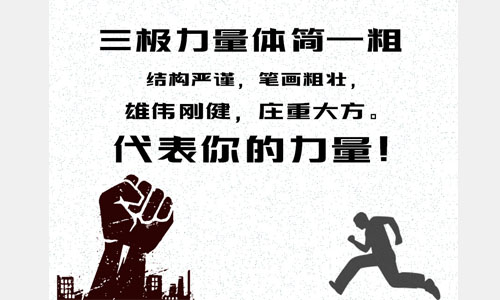
三極力量體簡(jiǎn),字形扁方、結(jié)構(gòu)嚴(yán)謹(jǐn),筆畫粗壯、左右結(jié)構(gòu)有意夸張,富有張力。結(jié)構(gòu)新穎獨(dú)特、個(gè)性剛健有力,給人一種氣勢(shì)雄偉,莊重大方的感覺。適用于商業(yè)品牌的廣告、產(chǎn)品包裝設(shè)計(jì)、影視作品,界面設(shè)計(jì)。歡迎喜歡三極力量體的朋友前來下載使用。